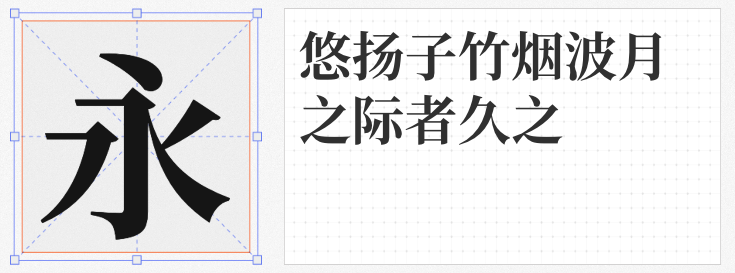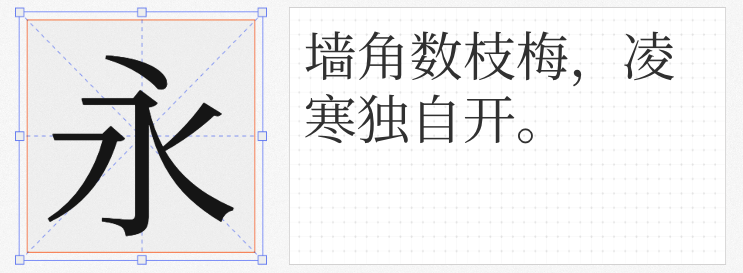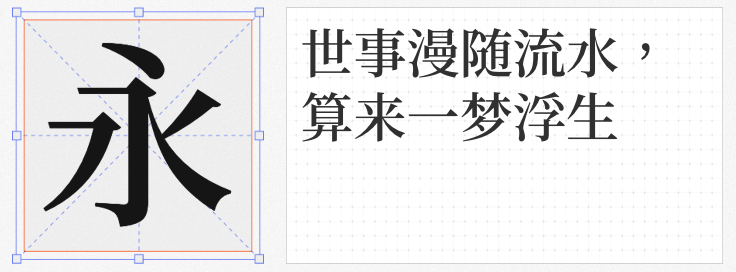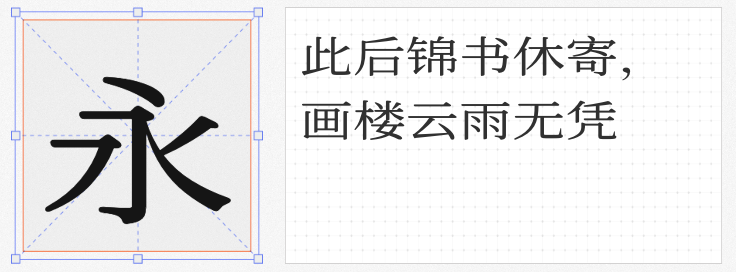
在东方设计语境中,宋体字以其独特的文化基因与现代适应性,始终占据着视觉传达的核心地位。本文精选四款免费商用宋体——寒蝉锦书宋Wide Regular、思源宋体 CN Regular、繁媛明朝 SB、昭源宋体 Bold,它们不仅延续了宋体字横细竖粗的经典美学,更通过结构优化与技术创新,为当代设计提供了兼具文化深度与实用价值的解决方案。
一、寒蝉锦书宋Wide Regular
这款基于思源宋体深度优化的字体,通过0.3mm圆角处理消解了传统宋体的锐利感,横竖笔划的粗细比调整为1:2.8的黄金比例,使中英文排版更具呼吸感。特别适合文化类品牌视觉系统与书籍装帧设计。字体名称“锦书”既暗含“锦上添花”的装饰性,又寄托“前程似锦”的美好寓意。
二、思源宋体 CN Regular
作为Adobe Type联合Google发布的泛CJK字体,思源宋体以7字重、65,535个字符的超大字库重新定义了开源字体的专业标准。其横细竖粗的典型宋体结构中,融入了0.5%的字面扩张设计,使小字号显示时依然保持清晰轮廓。该字体支持简繁日韩四种语言体系,成为跨国品牌视觉统一化的理想选择。
三、繁媛明朝 SB
针对中文简繁转换的痛点,这款基于源样明体开发的字体通过“一简对多繁”的智能映射技术,解决了传统字体在转换过程中出现的字符缺失问题。其保留的思源宋体骨架中,对折角处进行15°圆弧优化,使文字在保持传统韵味的同时更适配数字屏幕显示,特别适合需要兼顾两岸三地市场的文化类产品包装。
四、昭源宋体 Bold
作为昭源黑体的配套宋体,这款字体通过1.2mm笔划加粗处理强化了视觉冲击力,同时采用“横细竖粗+斜笔减细”的复合结构,确保在小字号显示时仍能清晰可辨。其开放的OpenType特性支持多语言排版与字形替换,从移动端界面到户外广告牌均能完美适配,成为新媒体时代的高效视觉工具。
这四款字体通过结构创新、比例优化与智能技术应用,构建起从传统印刷到数字媒介的完整宋体解决方案。它们不仅延续了宋体字的文化基因,更以免费商用的开放姿态,为设计师提供了突破创意边界的优质选择。